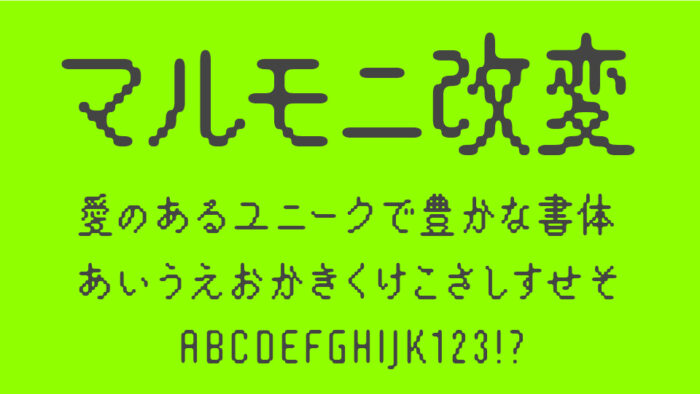
マルモニ改変
マルモニ改変フォントは、「マルモニカ」フォントをベースとして、角丸・斜体・ソリッドなど10種類以上のバリエーションに展開されたドットフォントです。
「マルモニカ」の持ち味を大切にしながら、幅広いバリエーションに広がることで、見る人に楽しさや遊び心を感じさせるフォントに仕上がっています。
以下3種類のサンプルですが、配布サイトでは他にも数多くのバリエーションが用意されているので、ぜひ見てみてくださいね。